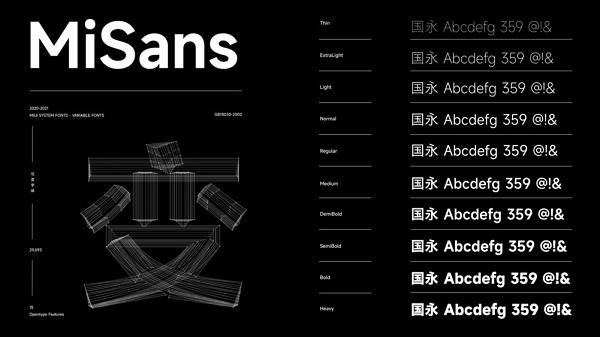
小米miui13系统misans字体
miui misans官网简介:
MIUI 13 采用全新系统字体 MiSans;笔型平直有力,设计更加简约,减少视觉负担,更有利于屏幕显示。共包含29,093个字符,支持多种语言。MiSans 提供了多种 OpenType 功能,可根据特定需求来选择不同形态的字符,例如某些标点符号可以根据周围字母的形态自动调整至合适的位置。MiSans字重齐全,层级清晰,10个字重全部开放下载,供全社会免费商用。
字体特点:
字体功能调用及实现:
font-feature 属于 Opentype 中的高级排版功能,也就是可以让字体排版更加精致,符合实际设计、开发需求,可根据特定设计需求选择不同的字体形态。大部分软件都可以通过 Opentype 面板访问此功能。(部分特性在MIUI系统应用中不会默认生效)